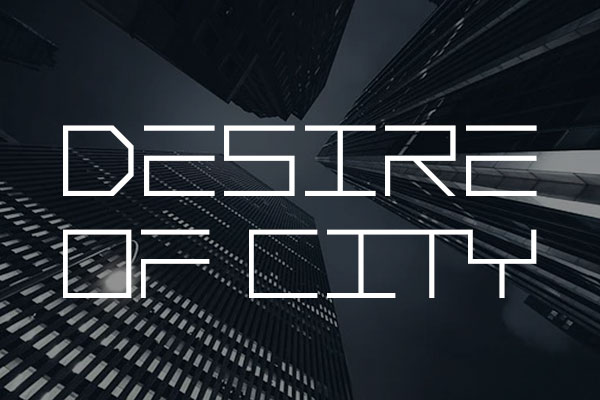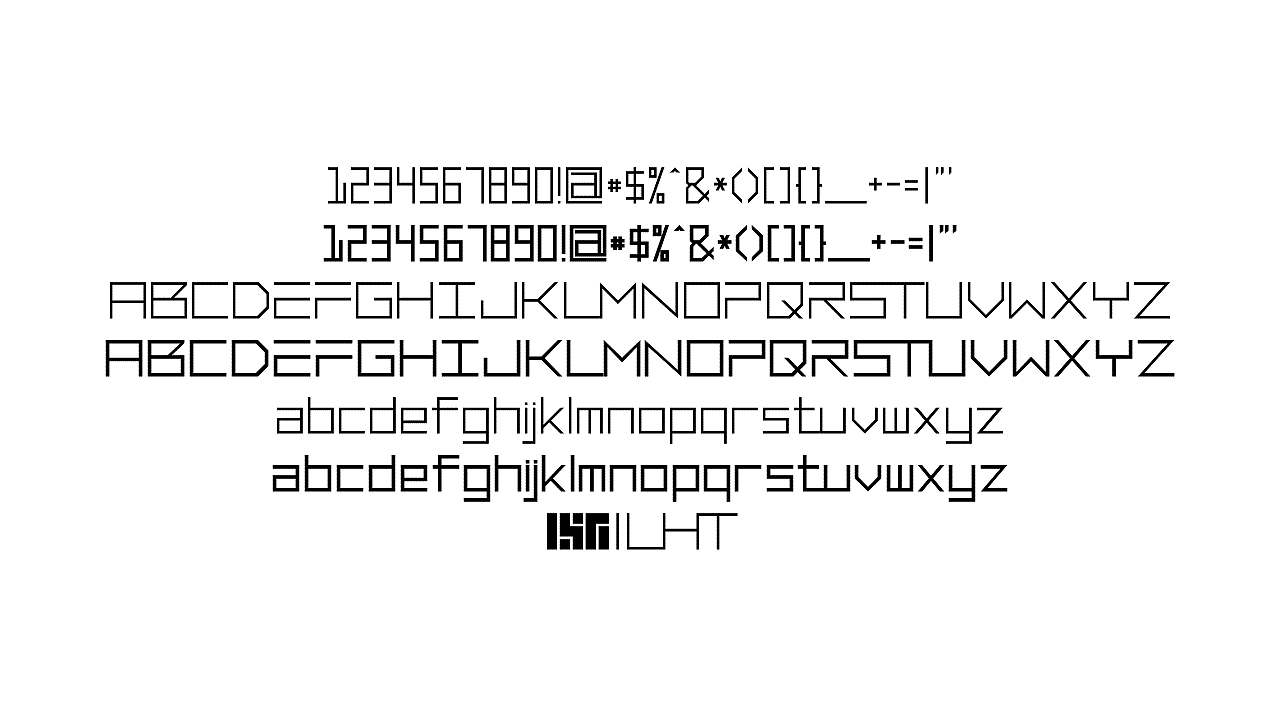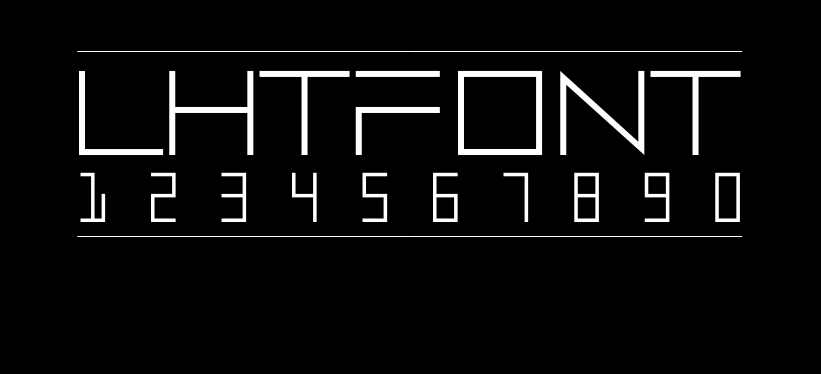
LHTFONT
LHTFONT的作者是宜春的LHT02,作者自称该字体为本人困在家里闲得慌做出来的一款英文字体,其实这个字体很早以前就准备去做了,打算是用来配合自己的作品用的。”₤”被替换成了作者自己的LOGO,用艺术字体的一般也不会去闲的专门去输入这个符号。大写字母”L”与”T”以及小写字母”t”会连字,这是故意的。整个字体里面除了几个半辈子不会去打出来的符号以外不含有任何曲线。字体斜线的宽度可能会粗细不一,已经尽力了。。。